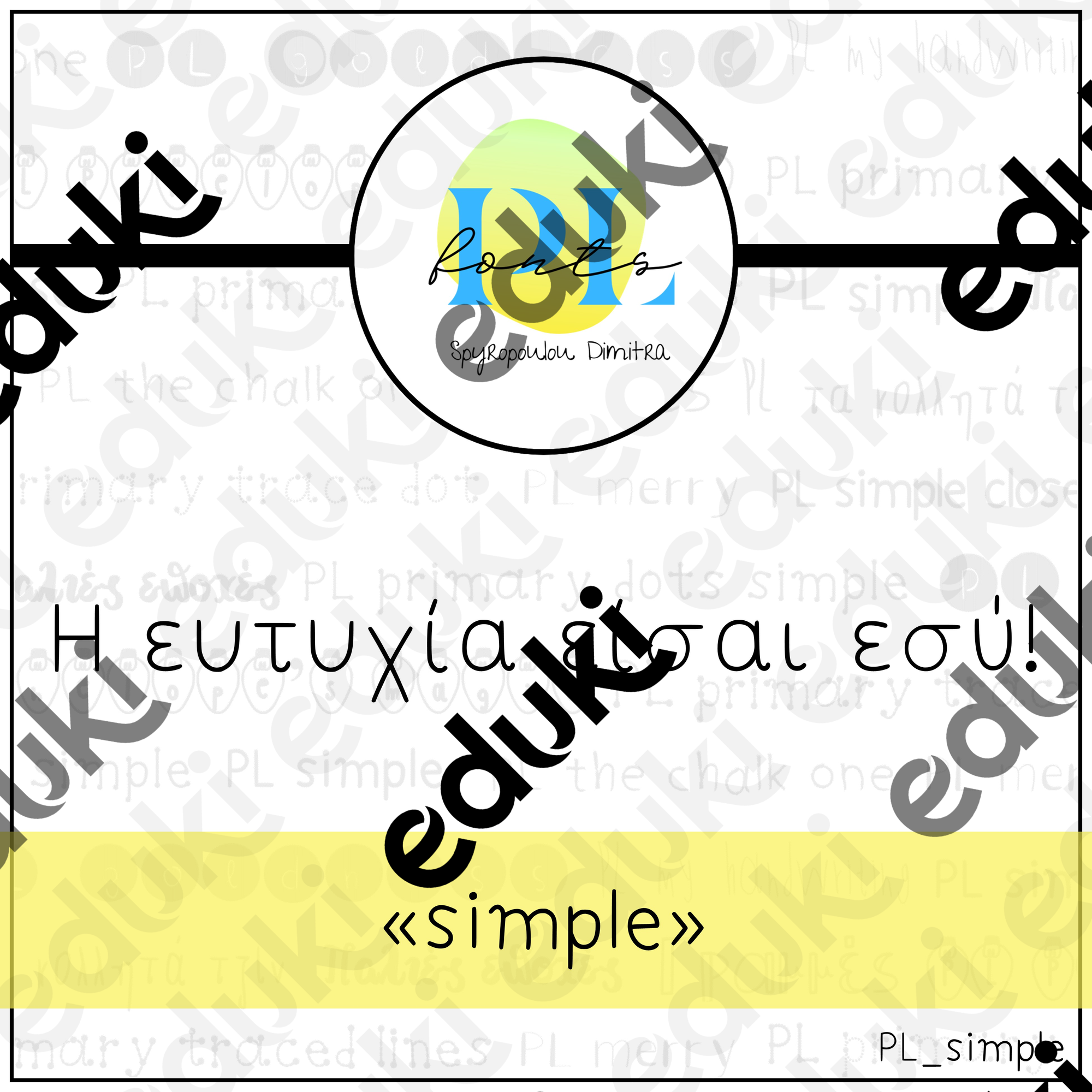
Αυτή η γραμματοσειρά ονομάζεται "simple" (απλή) και αποτελεί γραμματοσειρά κειμένου (text font). Είναι γράμματα που έχουν κανονική ένταση και είναι υπέροχη για εκπαιδευτικούς λόγους, καθότι τα γράμματα γράφονται όπως συνηθίζουν να τα μαθαίνουν τα παιδιά στο σχολείο.
Η γραμματοσειρά περιλαμβάνει ελληνικούς χαρακτήρες καθώς και αγγλικούς, αριθμούς, μαθηματικά σύμβολα και σημεία στίξης.
This font is called "simple" and it's a text font.
This font includes Greek characters as well as English ones, numbers, mathematical symbols, and punctuation marks.
PL font_Simple (english and greek font)